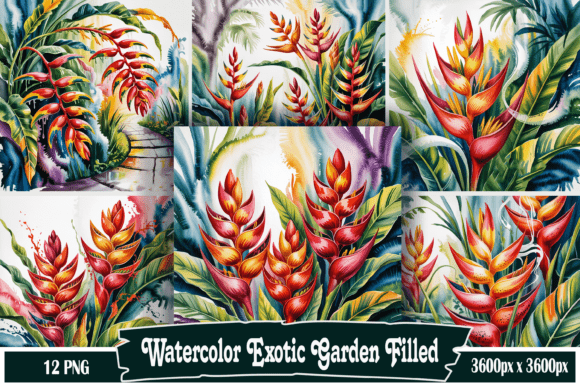
Watercolor Exotic Garden Filled
Doğru tasarım öğelerini bulmak zor olabilir, ancak Watercolor Exotic Garden Filled, çalışmanızı anında bir üst seviyeye taşıyan olağanüstü bir koleksiyon sunar.